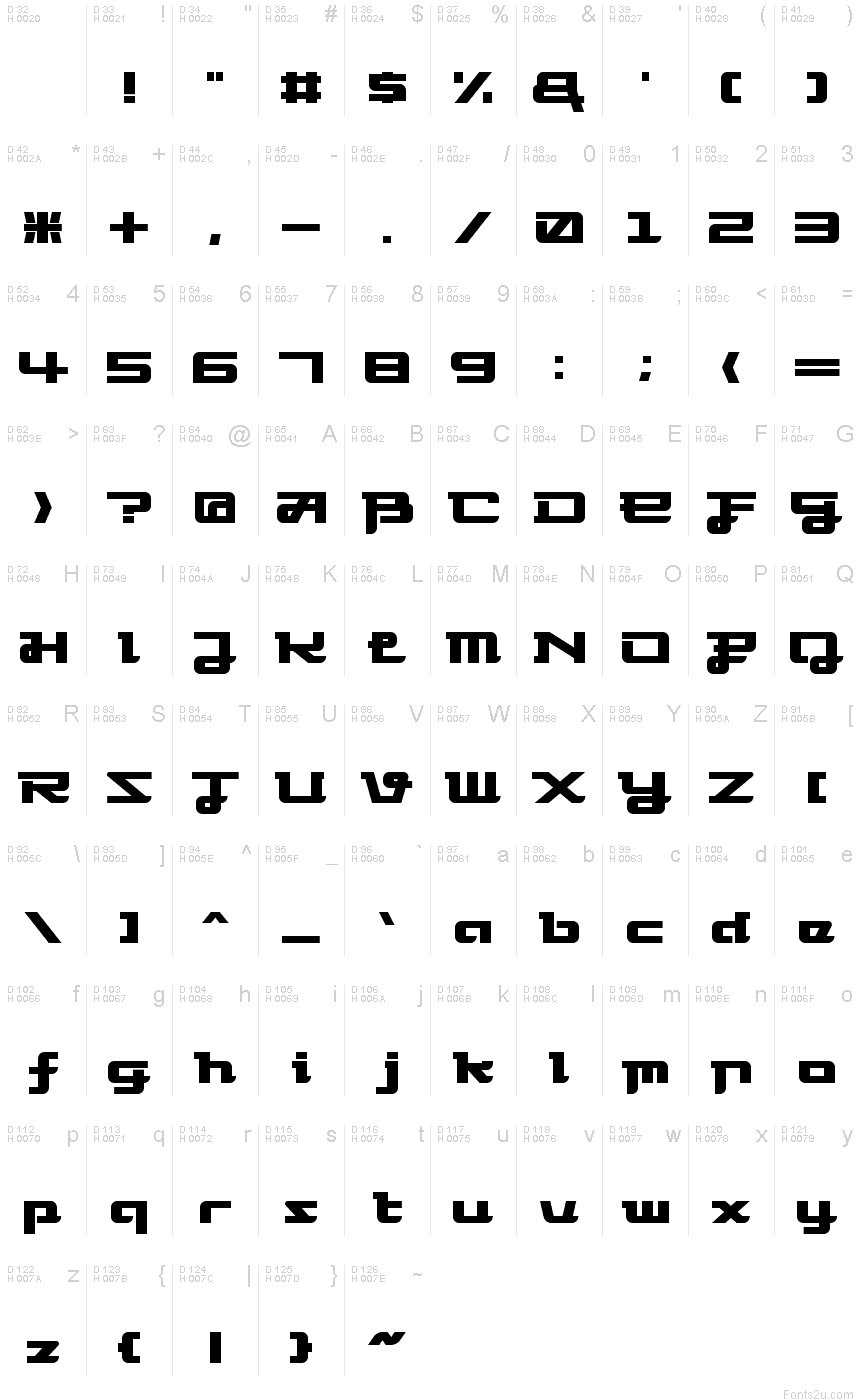
Flyermix od Flop Design to darmowy, retro-futurystyczny krój pisma typu display, charakteryzujący się spokojnym, płynnym rytmem i masywnymi znakami, które łączą się niczym elementy własnego logotypu. Litery nawiązują do estetyki klubowej grafiki początku XXI wieku – zaokrąglone rogi, głębokie wcięcia i długie poziome linie nadają krojowi kompaktowy, mechaniczny charakter.
Sprawdza się na plakatach, okładkach płyt, ulotkach, grafikach streetwearowych i tytułach, wszędzie tam, gdzie darmowy font potrzebuje wyrazistego, syntetycznego brzmienia, bez wrażenia sterylności czy sztuczności. Szczególnie dobrze sprawdza się w krótkich nagłówkach i znakach słownych, ponieważ dzięki połączeniom i ciężkim, blokowym kształtom nawet kilka liter sprawia wrażenie zaprojektowanej grafiki, a nie zwykłego tekstu.